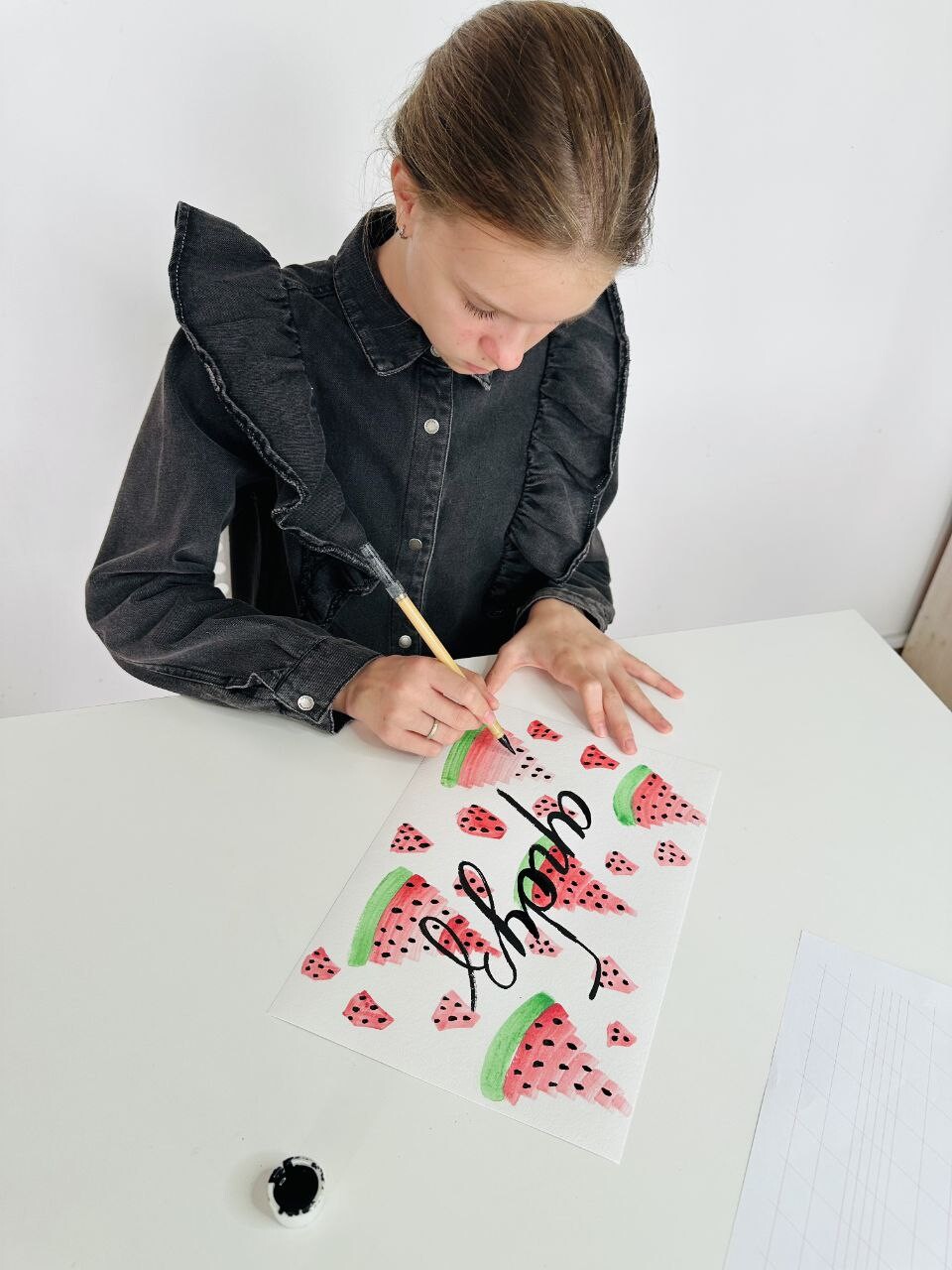
Как исправить почерк ребенку в 10 лет и старше: реально ли улучшить почерк подростку?
Почерк в 12 лет: последний шанс или новое начало для обучения каллиграфии?
Бытует мнение, что после 10 лет почерк уже «сформировался» и менять его бесполезно. Как специалист по красивому письму, скажу честно: это миф.
Да, в 10–12 лет мы часто сталкиваемся с педагогической запущенностью — когда ребенку не показали правильную основу в начале обучения. Он пишет так, как понял или придумал сам, а ошибки закреплялись годами.
Но именно в подростковом возрасте мозг становится более осознанным, и коррекция почерка у ребенка может пройти даже быстрее и эффективнее, чем у первоклассника.
Почему ребенок пишет неразборчиво: когда скорость письма разрушает почерк
В средней школе ребенку нужно писать быстро. Если фундамент был слабым, при ускорении всё начинает «сыпаться».
Буквы становятся неразборчивыми, соединения исчезают, а почерк скорописью в экзаменационных бланках превращается в нечитаемый шифр.
Это ведет к потере уверенности и снижению успеваемости по всем предметам, ведь почерк и развитие мозга тесно связаны.
Как развить почерк у подростков: осознанный подход и уроки каллиграфии
Здесь не работает давление сверху. Подростку важно понимать смысл: зачем мне это?
Мы объясняем, что каллиграфия развивает мышление, концентрацию внимания и волю.
Наш подход включает несколько этапов.
Анализ структуры
Мы рассматриваем письмо как систему: ритм, логику построения букв и наклон.
Профессиональные инструменты
Мы используем инструменты «взрослой» каллиграфии — перо, брашпен или качественную ручку для каллиграфии.
Это вызывает новый интерес к процессу. Для подростка это уже не детская игра, а освоение мастерства.
Исправление вектора
Даже в 12 лет можно переучить руку писать букву О и всю овальную группу правильно, против часовой стрелки. Это мгновенно добавляет письму ясности и скорости.
Пример моей старшей дочери Славяны, которая в 16 лет вела конспекты идеально ровным, быстрым и осознанным почерком, подтверждает: результаты после курса каллиграфии — это навык на всю жизнь.
Никогда не поздно пройти курс по каллиграфии и вернуть себе этот инструмент развития интеллекта. Почерк — это развитие мозга, и движение руки всегда можно сделать более уверенным и красивым.